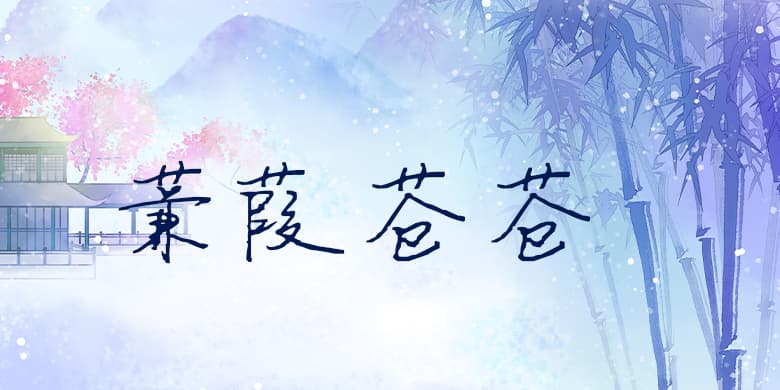
方正手迹-蒹葭苍苍
品牌:方正手迹设计师:赵倩发行时间:2020字库编码:大陆简体(GB2312-80)分类:常规书写·硬笔字体属性:精品字
方正手迹-蒹葭苍苍
蒹葭苍苍这款字体线条柔和灵动,转折多用圆笔,字形舒展大方,气质出尘,古典雅致,文艺气息浓厚。适用于文艺类的书刊、品牌广告和产品包装设计,以及社交网络的个性化用字。